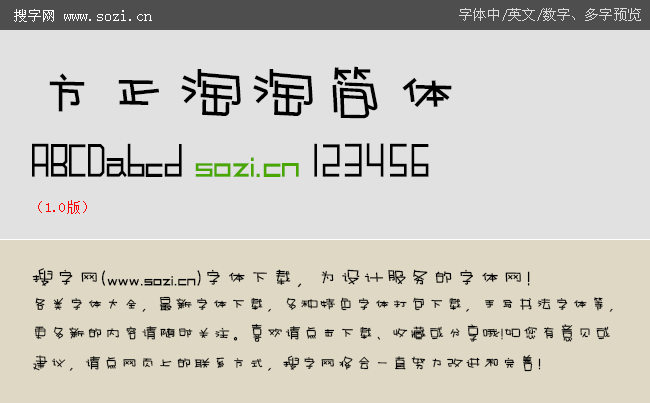
方正淘淘簡(jiǎn)體
搜字網(wǎng)提供一款可愛(ài)的卡通字體方正淘淘簡(jiǎn)體下載,方正淘淘簡(jiǎn)體字體,這是一款調(diào)皮的字體,字體效果呈無(wú)規(guī)則狀態(tài),大小不一,看似歪歪扭扭,卻也不失可愛(ài),比起整整齊齊的字體還是比較新鮮的,適用于廣告設(shè)計(jì)、兒童畫冊(cè)設(shè)計(jì)、包裝印刷、產(chǎn)品設(shè)計(jì)等應(yīng)用。